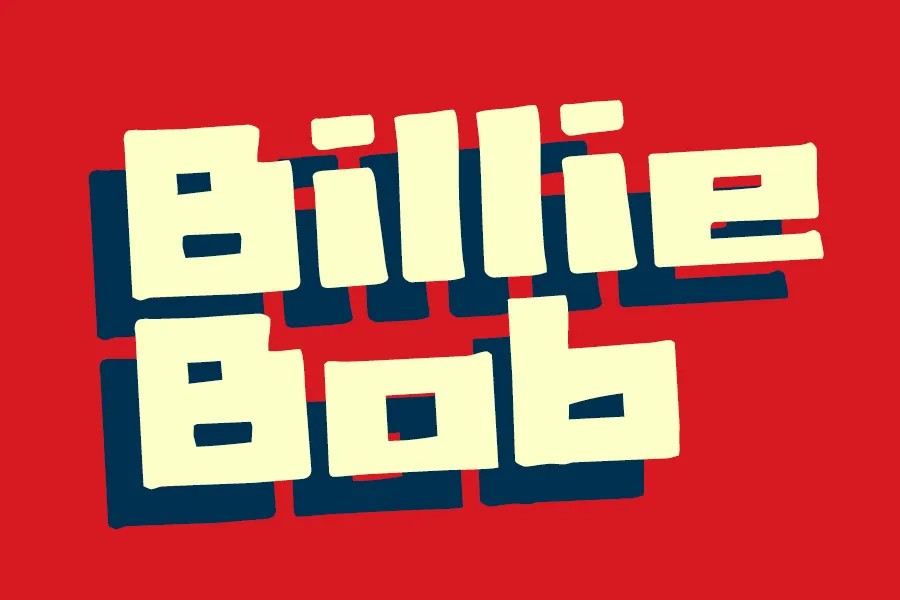
A Billie Bob Font é uma escolha ideal para projetos nostálgicos que exigem personalidade e destaque imediato. Criada pelo designer Hamilton, esta fonte atua como um elo entre a cultura moderna e as marcas digitais do passado. Ideal para design de flyers, posters ou mesmo t-shirts, a Billie Bob oferece uma aparência retro enquanto mantém o estilo contemporâneo e fácil de ler, tornando-a perfeita para criar um impacto visual notável em qualquer projeto que tenha como objetivo chamar atenção. Seja você designer gráfico ou mestre de festa, esta fonte estará sempre ao seu lado, garantindo uma experiência nostálgica sem comprometer a legibilidade e facilidade de uso do design moderno.